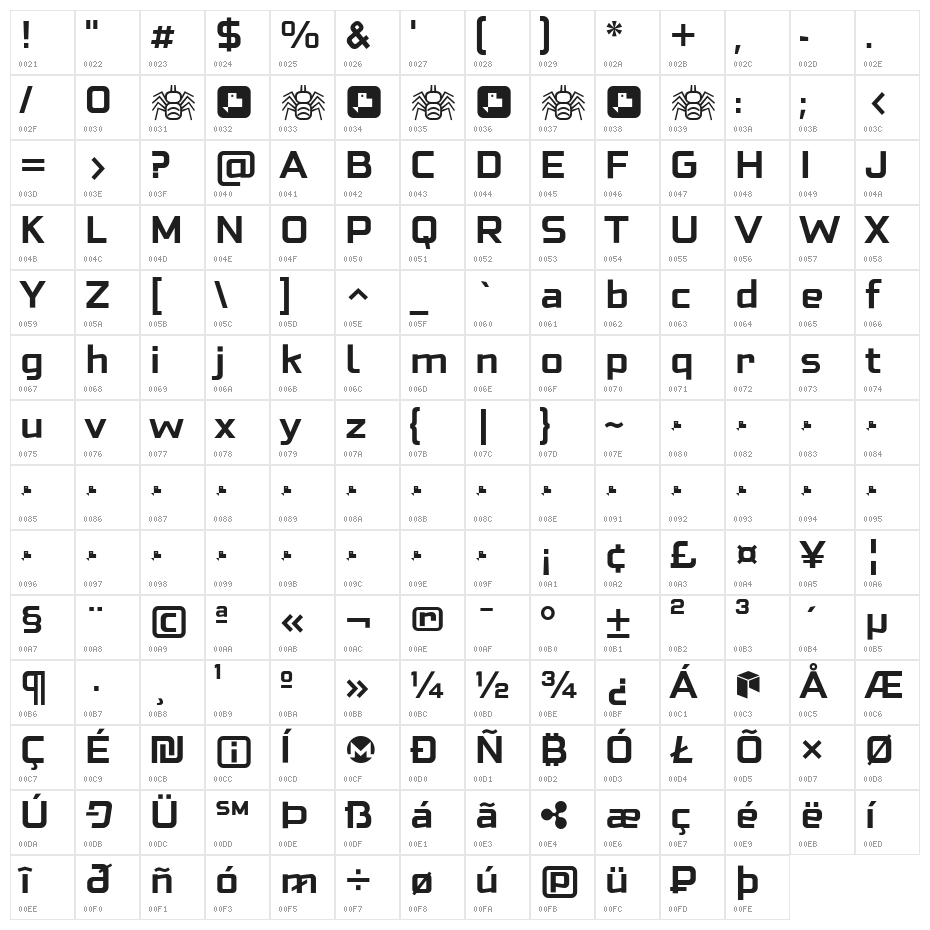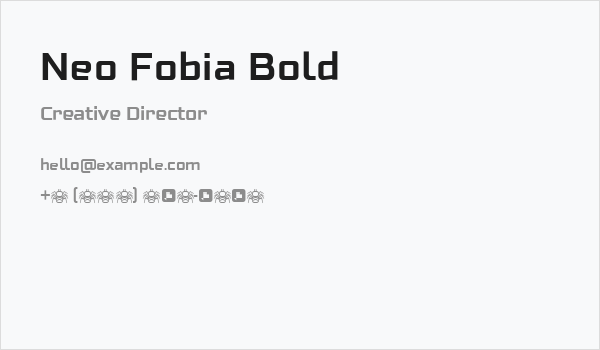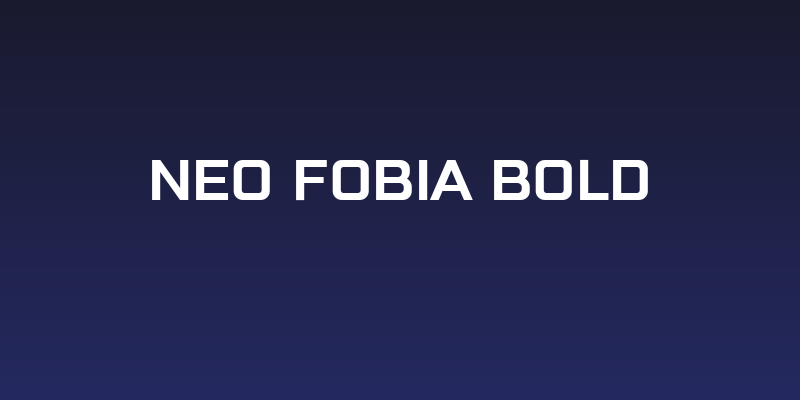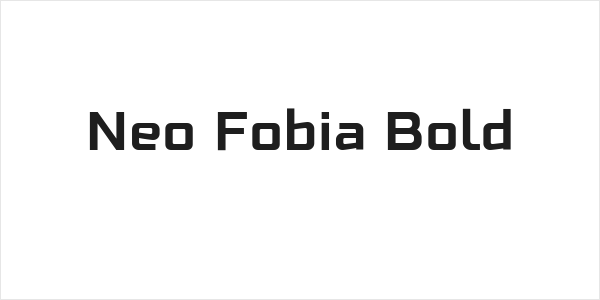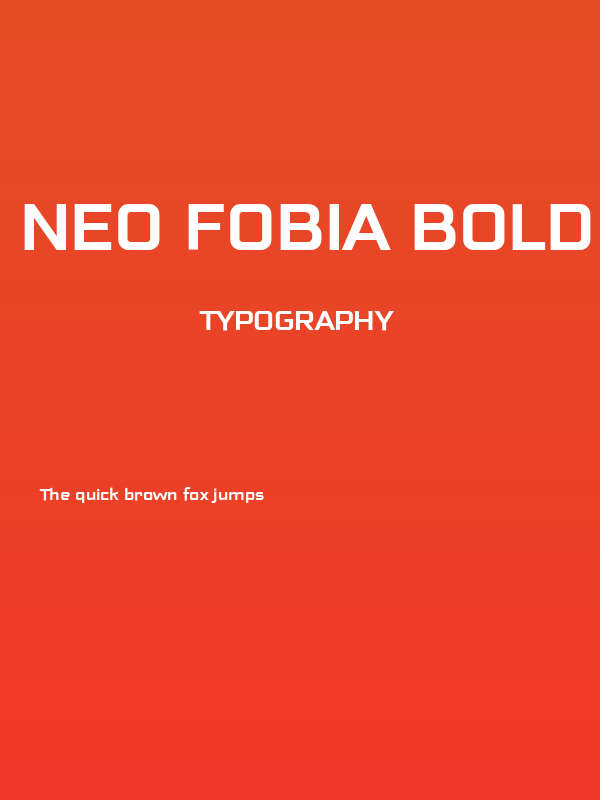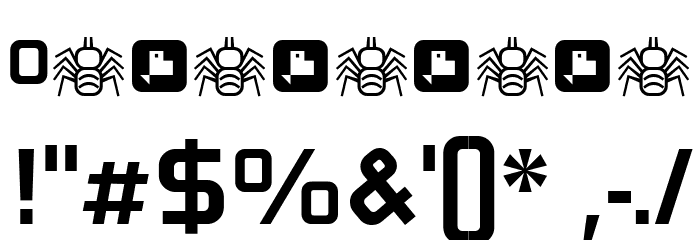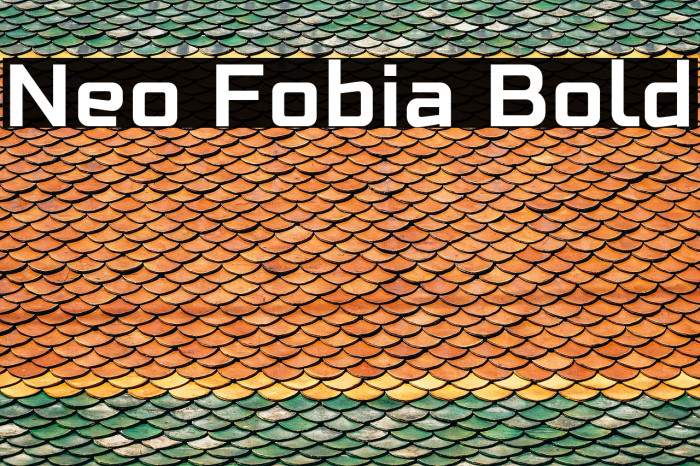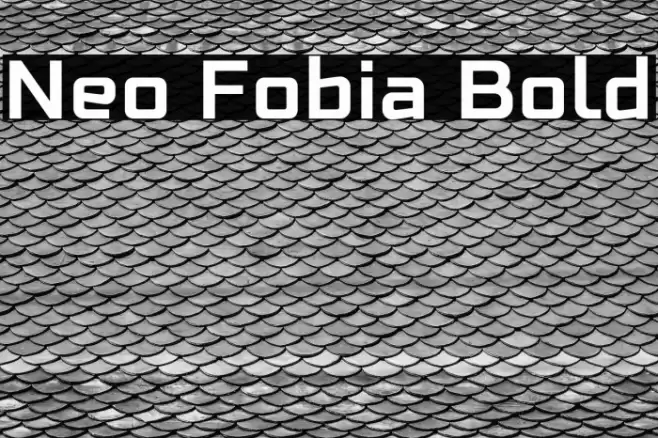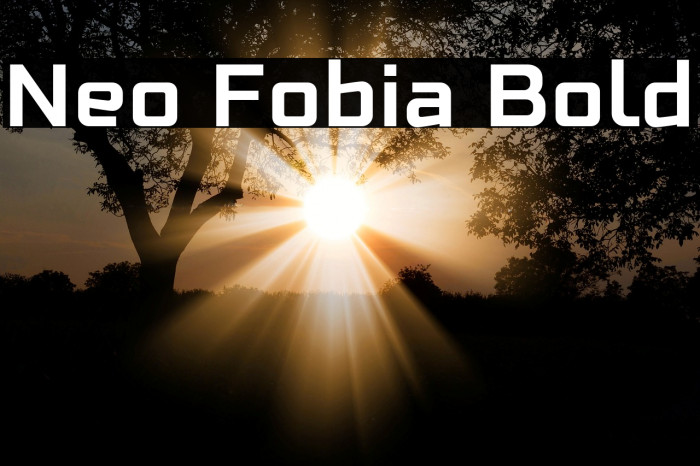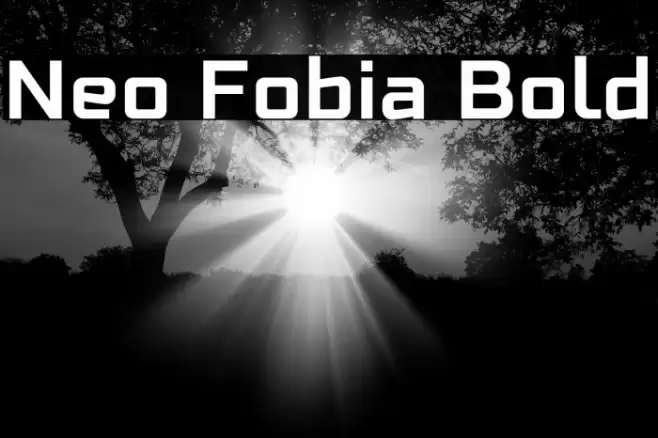
Neo Fobia Bold Font
| Caso de uso | Headlines, Logos, Digital Interfaces |
| Projetos propostos | Ideal for technology branding, modern advertising, digital interfaces, and futuristic designs. |